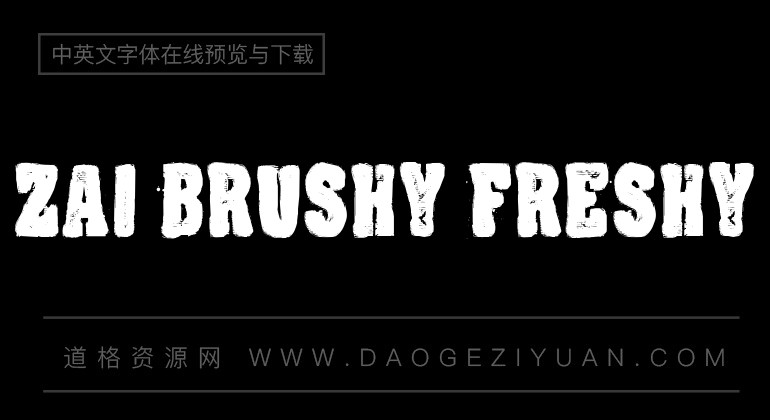
? Brushy Freshy 是一款流行的手写字体,它拥有温暖、活泼、自然的特色,适合用于卡片、海报、T恤等各种设计中。它的字体特点是:每个字母都有一个细节,比如有折角、钩线、横线等,使得它看起来更加的有趣,也更容易让人记住。此外,它还有一个特别酷的特性,那就是可以调整字体大小,这样就可以根据你的设计需要调整字体大小,让你的设计更加精美。内容介绍
zai Brushy Freshy是一款非常不错的手写艺术字体,具有很好的视觉感,适合于文化类的宣传设计、商业类品牌的广告和产品包装设计以及个性化文字排版等较多场景。